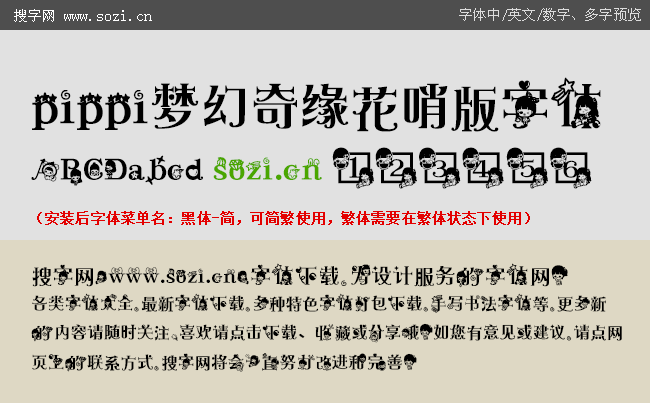
pippi夢(mèng)幻奇緣花哨版字體
搜字網(wǎng)給大家提供一款pippi夢(mèng)幻奇緣花哨版手機(jī)中文字體下載。這款手機(jī)字體是在華康飾藝體筆畫(huà)間插入了可愛(ài)的卡通圖案。華康飾藝體是一款帶有西方古典美的字體,橫細(xì)豎粗,起筆落筆處加有西方特色的櫬線裝飾,跟西方的花體字很類(lèi)似。加入了卡通圖案后更增添了趣味性,特別適合喜歡手機(jī)字體個(gè)性一些的朋友在手機(jī)上安裝使用。